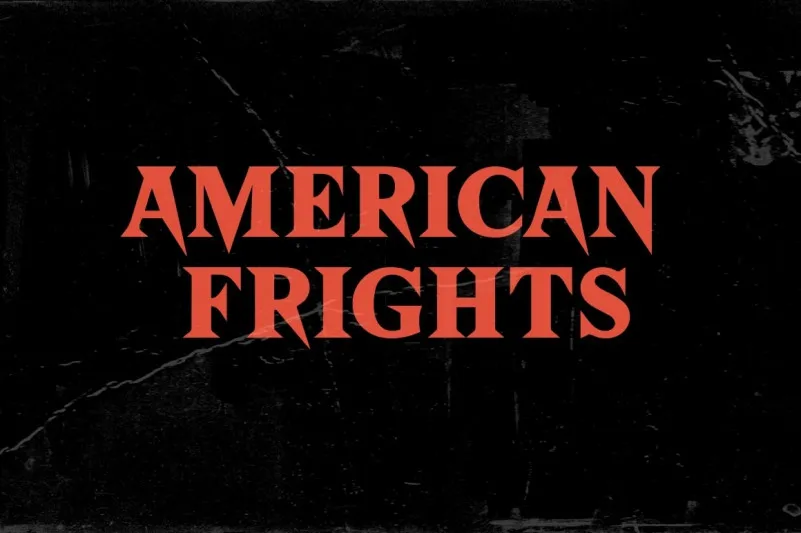
Você encontrou a American Frights Serif Font aqui, uma opção moderna com elementos vintage para designers e criativos. Esta elegante e versátil fonte serif contém alternativas e ligaturas, tornando-a perfeita para logos, citações, convites de casamento, postagens de blog, Instagram e muito mais! Transforme sua obra em algo que nunca imaginou que era possível com apenas um pouco de refinamento. A American Frights é uma tipografia projetada para o gênero do terror e emoção, perfeitamente adaptada tanto para logotipos e identidade visual como para headlines e textos sobre roupas, noivas e outros temas. A fonte tem uma quantidade significativa de características e alternativas ornamentadas tanto para letras maiúsculas quanto minúsculas, oferecendo-lhe a liberdade necessária para criar designs que surpreendem. Se você deseja manter um estilo clássico, ou se está pronto para dar um toque refinado e elaborado às suas obras de arte, esta fonte é perfeita. Hamilton foi o criador desta inovadora tipografia, garantindo que a American Frights tenha uma presença única no mundo do design gráfico.